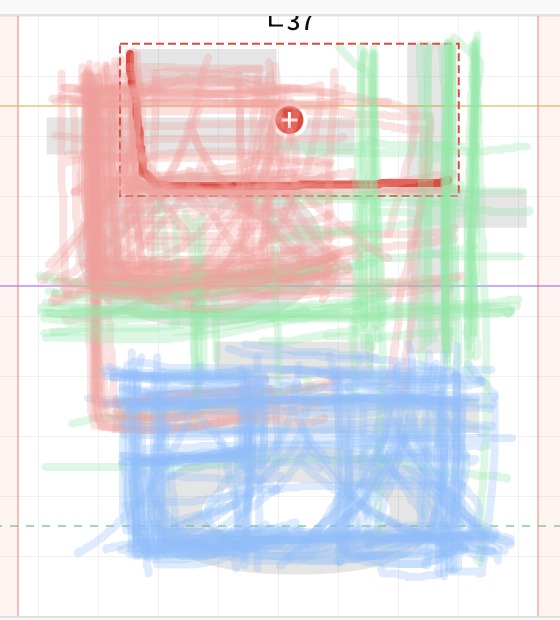
손글씨 폰트 기본 획작업을 마무리
GAN Generative Adversarial Network 적대적신경망을 만들어서 테스트 하는 방식이 아니라 이미지가 아닌 벡터 획 기반으로 손글씨처리를 하는 방식으로 지난 3년간 작업을 했다가 안했다가 하던 중에 에디터를 일단 만화폰트 위주로 먼저 작업을 해보고 있습니다.
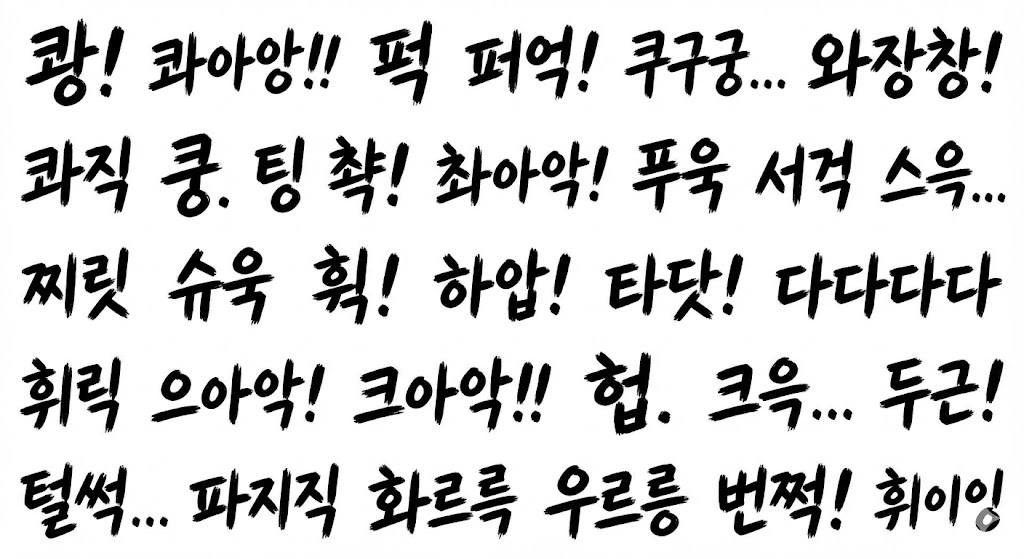
만화폰트는 잘 만들어집니다. 하지만 목표는 그게 아니기 때문에 실제로 폰트작업에서 붓의 모양에 따른 획의 시작과 끝 획의 필봉을 표현하는 방식에 따라 서체의 틀이 잡히고 구성에 있어서도 중앙축성과 기필의 노봉성에 따라 분류를 하고 있어 모양이 변화에 따른 전체 균형을 잡는 형성범위를 구분할 수 있다.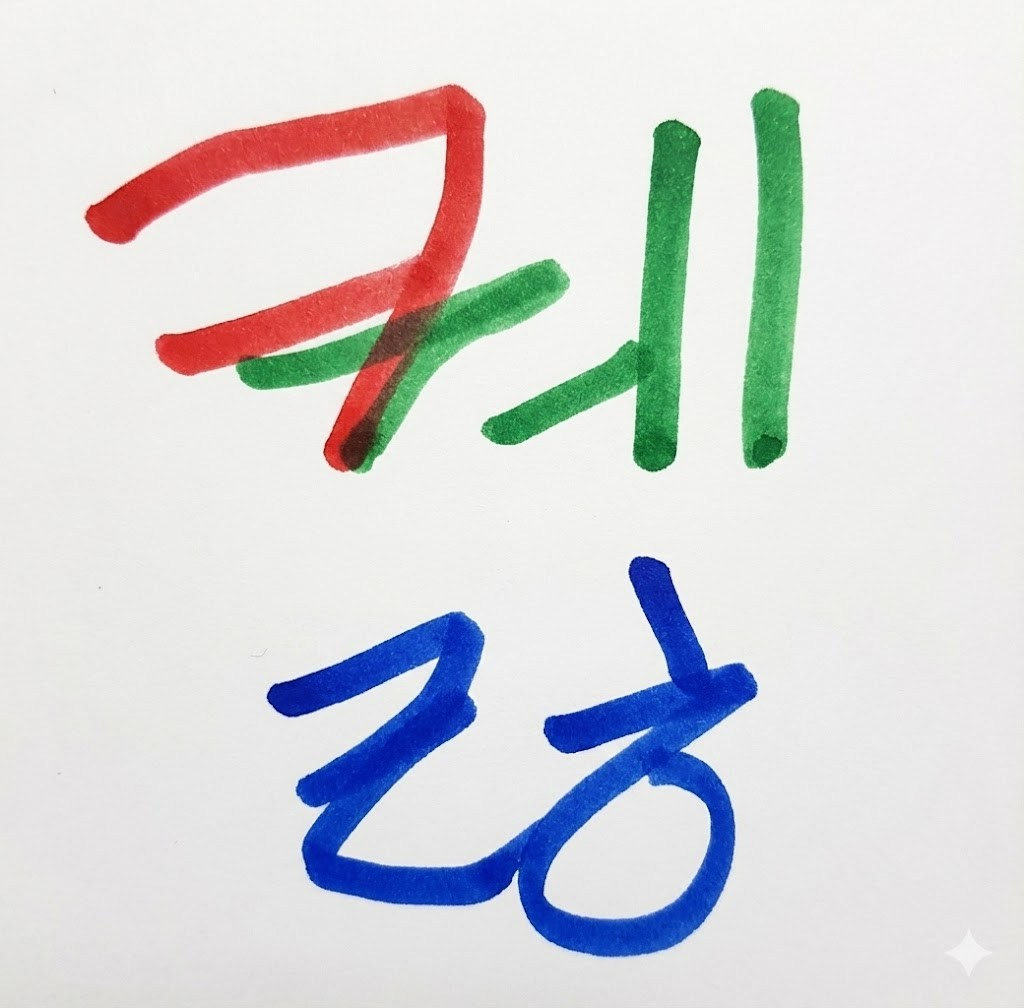
현재 작업은 폰트의 xray 로 글자의 모양에 따른 겹침이 있는 모든 좌표를 측정하고 획의 영역을 찾아내는 과정을 거쳐 이제 stroke 에서 shape 로 전환하는 2가지 유형의 글꼴 모양 즉 뼈대와 살을 나눠져 작업을 하는 것이고 곧 시작, 종료점에 따른 운필지점의 변화값을 더할 예정이다.
그래서 획에 어떤 모양이 붙느냐에 따라 붓펜이 되기도 마커펜이 되기도 하는 펜모양 대로 표현을 할 수 있는 폰트가 된다.